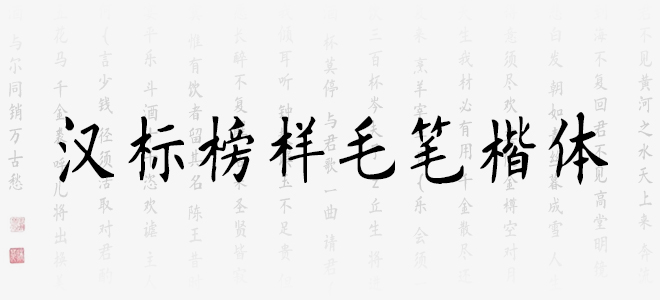
漢標(biāo)榜樣毛筆楷體的創(chuàng)意體現(xiàn)了雅俗共賞的審美追求,集古出新的藝術(shù)品質(zhì),清新自然的表達(dá)風(fēng)格,遵章循法的書(shū)寫(xiě)規(guī)范,歡迎喜歡漢標(biāo)榜樣毛筆楷體的朋友前來(lái)下載使用。
漢標(biāo)榜樣毛筆楷體